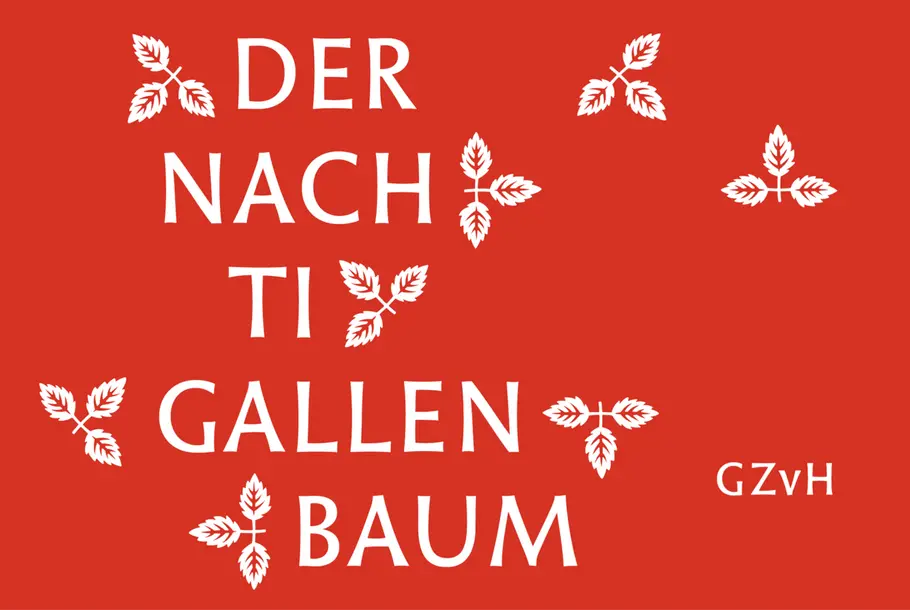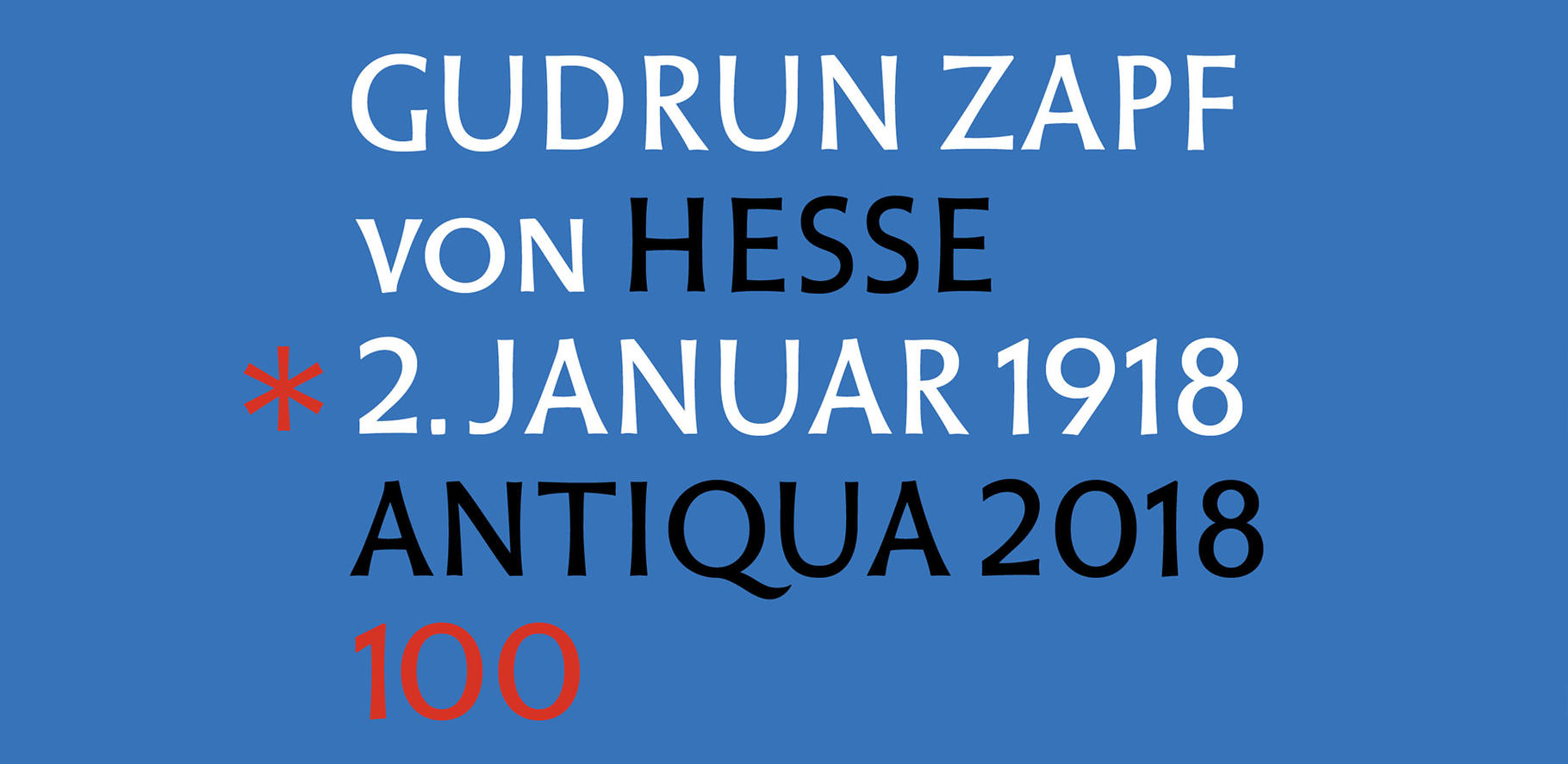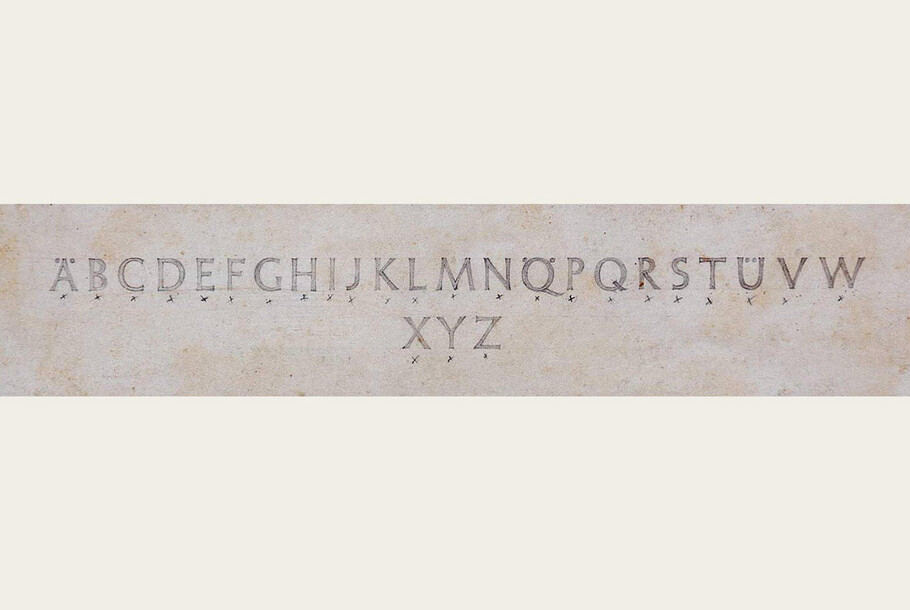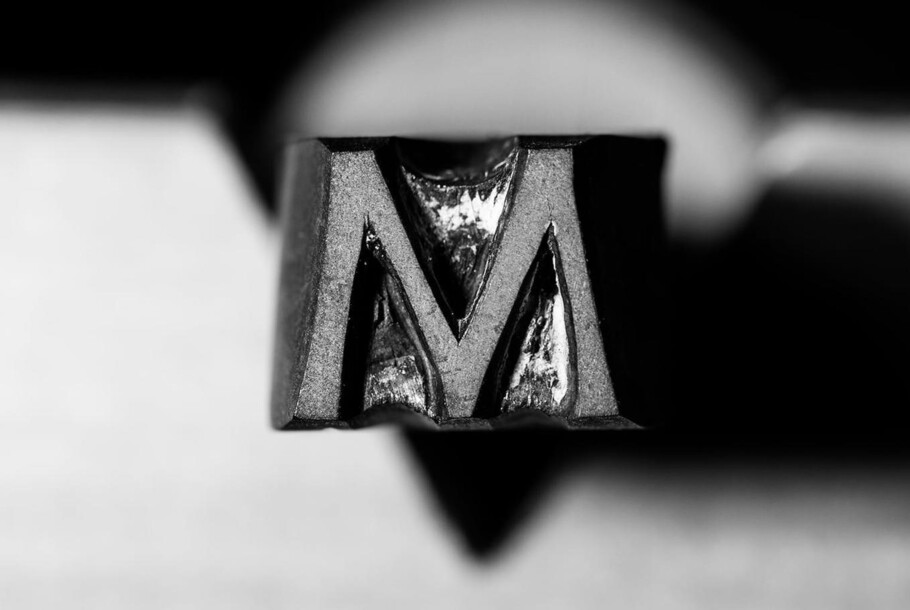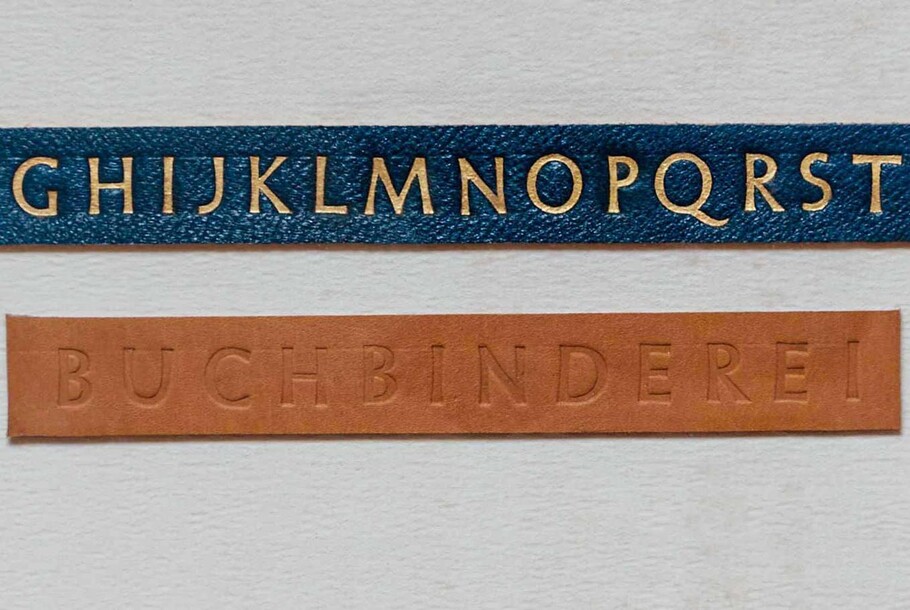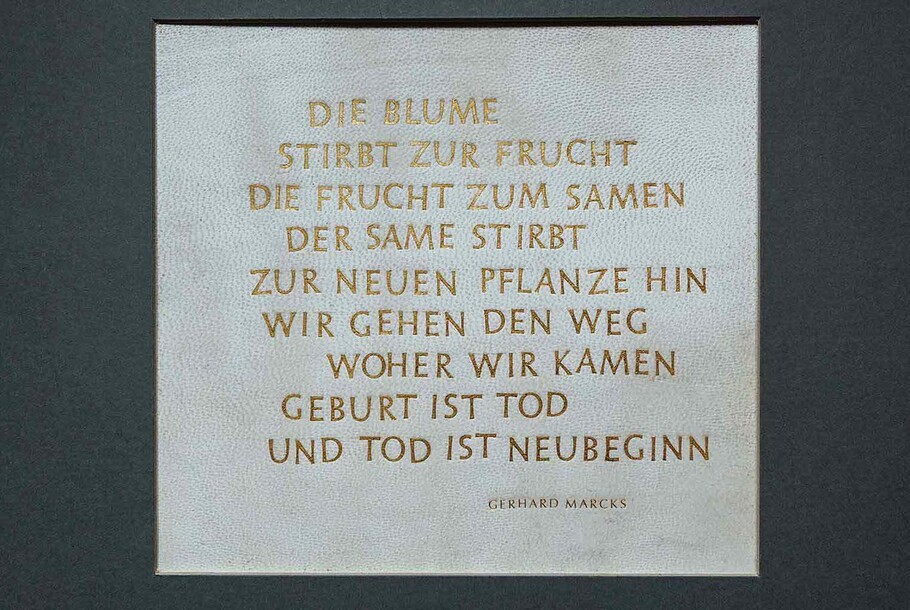
Hesse Antiqua™ zum 100. Geburtstag
Hesse Antiqua
Gudrun Zapf von Hesse, geboren am 2. Januar 1918, ist eine Frau mit vielen Talenten. Zuallererst – so würde sie sagen– ist sie eine gelernte Buchbinderin. Sie war aber auch als Schriftkünstlerin tätig, hat viele grafische Arbeiten geschaffen – und sie ist eine Schriftentwerferin. Zu ihrem 100. Geburtstag, erscheint diese Woche bei Monotype ein Alphabet, das sie schon vor 70 Jahren entworfen hat: Hesse Antiqua™. Ferdinand Ulrich erzählt von Ursprung und Digitalisierung der Schrift. Read English Version …
In den Wirren des Nachkriegsdeutschlands konnte sie nicht mehr in ihr Elternhaus in Potsdam zurückkehren. So zog Gudrun Zapf von Hesse Ende 1945 in eine hessische Kleinstadt. Ausgestattet mit einer Mappe stellte sie sich bei der Bauerschen Schriftgießerei in Frankfurt am Main vor. Dessen Direktor Georg Hartmann höchstpersönlich gab ihr die Möglichkeit eine eigene Buchbinderwerkstatt einzurichten und dort auch externe Aufträge zu erledigen. Bei Bauer lernte GZvH den künstlerischen Leiter Heinrich Jost und den Schriftentwerfer Konrad F. Bauer kennen, von denen sie viel über den Herstellungsprozess von Bleischriften erfuhr. Ihr freundliches Wesen und ihre Fertigkeiten wurden sehr geschätzt. Jost lobte sie als „perfekte Buchbinderin“ (in einem Empfehlungsschreiben vom 24. Februar 1947).
Eines Tages fasste sich GZvH ein Herz und stattete den Schriftschneidern einen Besuch ab. Zu dieser Zeit wurde das Schriftschneiden nicht von Frauen ausgeübt, und wenn es doch Ausnahmen gab waren sie bemerkenswert. Das Spiegelbild eines Buchstabens in einen bis zu 6 Zentimeter hohen Stahlstempel zu gravieren, ist der erste Schritt zur Herstellung von Bleibuchstaben. Es war ein akribischer Prozess, der kräftige Hände erforderte, um die Form eines Buchstabens mit Sticheln, Feilen und manchmal auch mit Gegenformen herauszuarbeiten. Der fertige Stempel erlaubte danach den Abdruck in einem weicheren Metallblock (meist aus Kupfer oder Eisen), der schließlich als Gießform diente. Im Wesentlichen dient diese Form (Matrize oder Mater) dem Schriftgießer als Vorlage für die Bleikegel.***
Abbildung 1, links: Bleibuchstaben wurden in einem aufwändigen Prozess hergestellt: von dem geschnittenen Stahlstempel zu der daraus eingeprägten Matrize (oder Mater), die als Gussvorlage für die Bleilettern dient. Rechts: Ein Stempelschneider mit seinem Werkzeug in der Schriftgießerei Bauer. Beide Abbildungen stammen aus Konrad F. Bauer: Wie eine Buchdruckschrift entsteht, Frankfurt/Main, 1950er Jahre (aus der Sammlung von Thomas Maier, Berlin).
GZvH interessierte sich allerdings weniger für einen vollen Setzkasten, sondern für das Schneiden von Stempeln, die sie mit Holzgriffen versehen zum Vergolden von Titelbeschriftung auf Buchdeckeln und Buchrücken aus Leder verwenden konnte. Dafür wollte sie ihren eigenen Schriftentwurf ins Spiel bringen. Unter der Anleitung des Stempelschneiders Josef Spahn lernte GZvH mit verschiedenen Gravierwerkzeugen und mit viel Geduld Buchstaben aus Messing zu formen (eine Stempelschrift für ihre Zwecke musste nicht in Stahl geschnitten werden). Ohne große Vorkenntnisse begann sie ihr eigenes Versal-Alphabet sowie die dazugehörigen Ziffern und ein paar wenige geometrische und figürliche Ornamente in 36 Punkt zu schneiden, eine amtliche Titelsatzgröße. Laut GZvH entstanden weder Probebuchstaben, noch mussten Zeichen ein zweites Mal geschnitten werden.
Abbildung 2, links: Das Werkzeug mit dem Gudrun Zapf von Hesse 1946 die Messingstempel anfertigte, hat sie bis heute aufgehoben (fotografiert vom Autoren in der Werkstatt von GZvH). Rechts: Mit Holzgriffen versehen, dienten die Buchstaben der Buchbinderin über Jahrzehnte als Werkzeuge zum Vergolden von Schriftzügen auf Bucheinbänden (fotografiert von Norman Posselt).
„ Dezente Kontrastverschiebungen und natürlich die handgeschliffene Natur verleihen diesem Alphabet eine spezielle Lebendigkeit.“ “
GZvHs erster Kontakt mit der Welt des Schriftentwerfens waren autodidaktischer Natur, mit Büchern von Edward Johnston und Rudolf Koch. Erst viel später (1941) besuchte sie an der Meisterschule für Graphik und Buchgewerbe in Berlin den Schriftunterricht von Johannes Boehland. Das Ergebnis ihres 1947 fertig gestellten Schriftschnitts ist ein Kind seiner Zeit: Serifenlose Buchstabenformen mit ordentlichem Kontrast und leichter Betonung der Strichenden. Dezente Kontrastverschiebungen, besonders hervorzuheben im S und natürlich die handgeschliffene Natur verleihen diesem Alphabet eine spezielle Lebendigkeit.
Abbildung 3: Eine seltene Darstellung der Hesse Antiqua: Schwarz auf Weiß. Bei diesem Rußabdruck wurden die Stempel in eine offene Flamme gehalten und die Buchstaben auf ein Blatt Papier übertragen (Fotografiert von Norman Posselt, aus der Sammlung von GZvH).
Die Buchstaben wurden erstmals für den Titelsatz eines Jahrbuchs verwendet, das die Bauersche Schriftgießerei anlässlich des 75. Geburtstages von Georg Hartmann herausbrachte (1946 gedruckt, 1947 gebunden). Der Name auf dem Umschlag und dem Rücken ist goldgeprägt, eine Spezialität von GZvH. In den folgenden Jahren produzierte sie weitere vergoldete Schriftzüge auf Buchrücken sowie Blindprägungen. Das Alphabet wurde zu ihrer exklusiven Hauschrift für besondere Anlässe.
Abbildung 4: Die Hesse Antiqua wurde erstmals für die Goldprägung des Buchumschlags einer Jubiläumsveröffentlichung zum 75. Geburtstag von Georg Hartmann verwendet, die von der Gießerei Bauer gedruckt und 1947 veröffentlicht wurde (Foto von Norman Posselt aus der Sammlung des GZvH).
Abbildung 5: Handvergoldungen auf Kalbspergament mit Messingstempeln gehören zu den Spezialitäten von GZvH. „Der Nachtigallenbaum“ ist ein bekanntes Werk, das mit Hesse Antiqua erstellt wurde. (Fotografie von Norman Posselt)
Abbildung 6: Die Präambel zur Charta der Vereinten Nationen hat GZvH aus der Hesse Antiqua in dickes aber weiches Papier blindgeprägt (Fotografie von Norman Posselt
* Eine etwas ausführlichere Biografie liefert der Abschlussvortrag des Autors auf der TYPO Berlin 2016
** Die Informationen über diesen speziellen Prozess bei Bauer stammt aus Konrad F. Bauers Wie eine Buchdruckschrift entsteht, Frankfurt/Main, Ende der 1950er Jahre
*** Dieses Handwerk wird in der Schriftgießerei Rainer Gerstenberg in Darmstadt noch immer praktiziert.